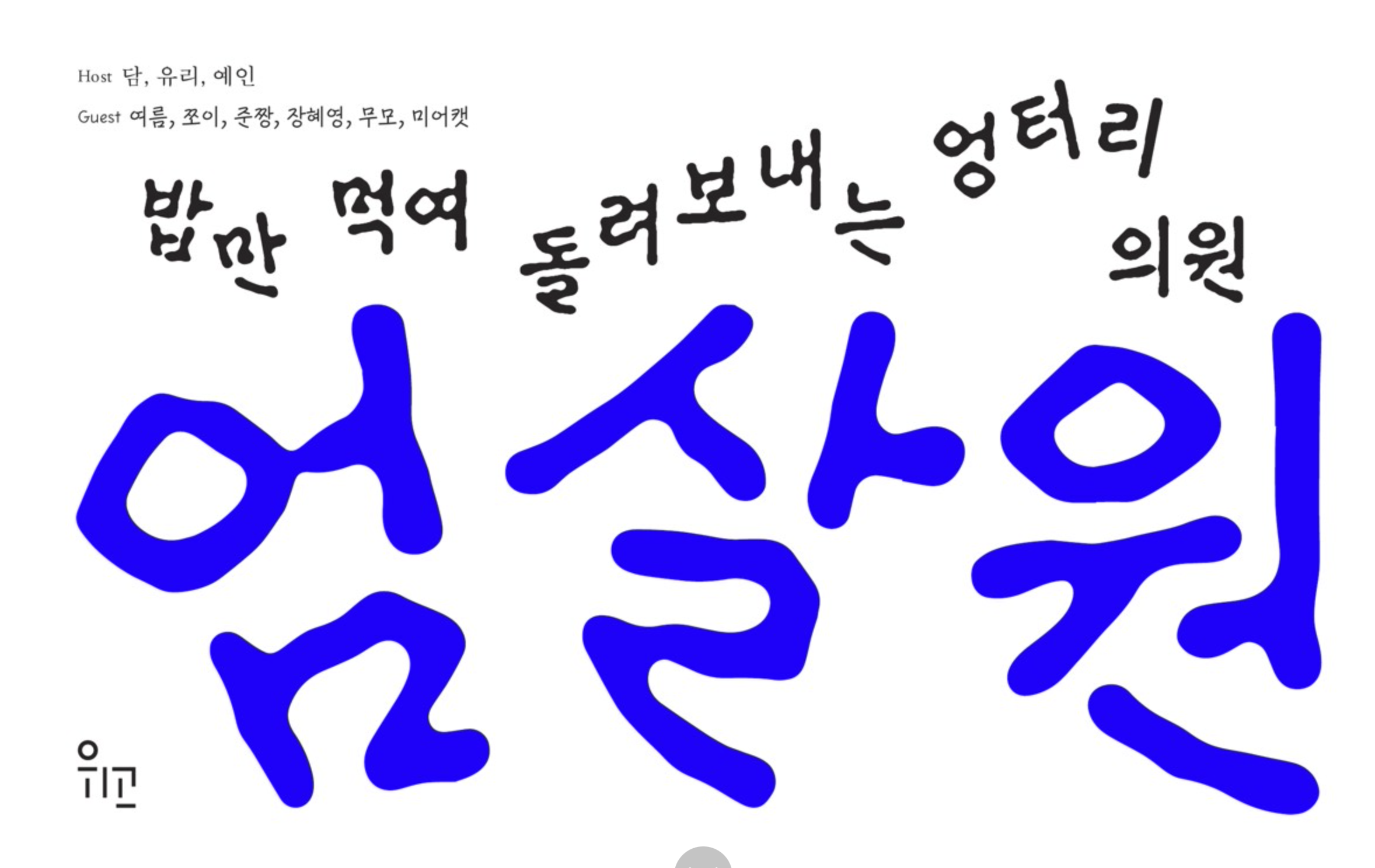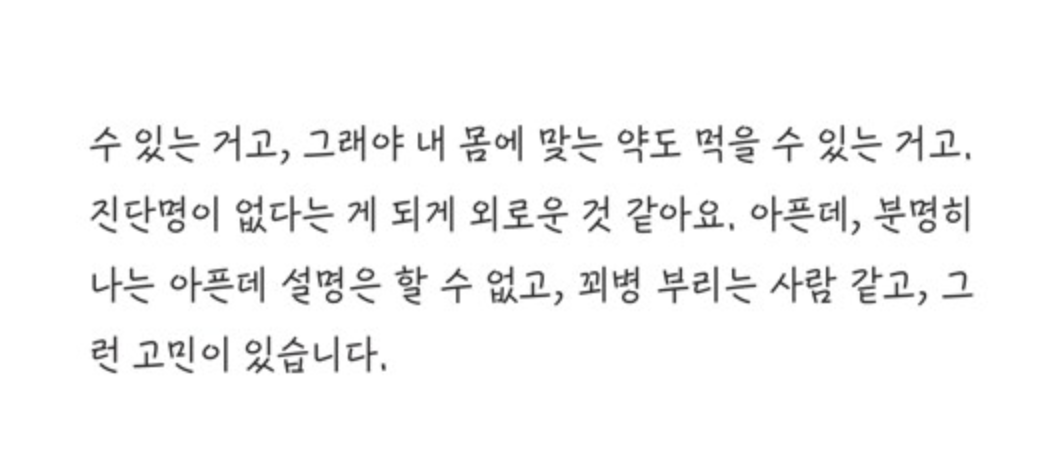
폰트 이름 tax*** 2023.12.15 무슨 폰트인가요? 궁금합니다 댓글 0 등록 sta*** 큰글씨 작은글씨 모두 HG시선들 같네요 https://www.sandollcloud.com/font/17089.html 큰글씨는 일러스트레이터 같은 데서 구불구불한 효과를 준 것 같아요 2023-12-15 답글 달기 댓글 더보기 쉽고 빠르게 가장 비슷한 폰트를 알고 싶다면? 이미지로 검색하기
큰글씨 작은글씨 모두 HG시선들 같네요 https://www.sandollcloud.com/font/17089.html 큰글씨는 일러스트레이터 같은 데서 구불구불한 효과를 준 것 같아요